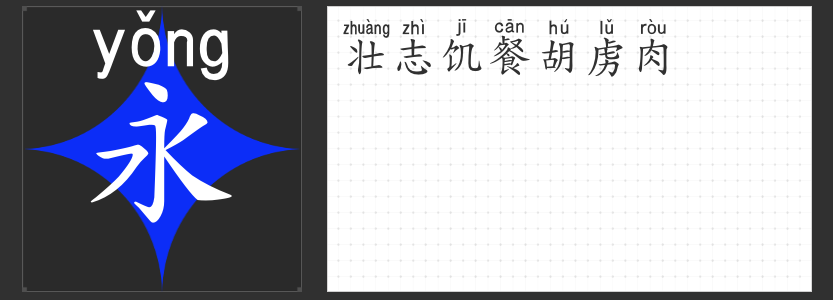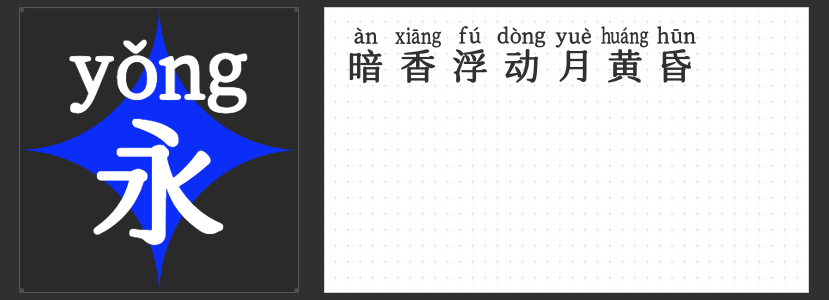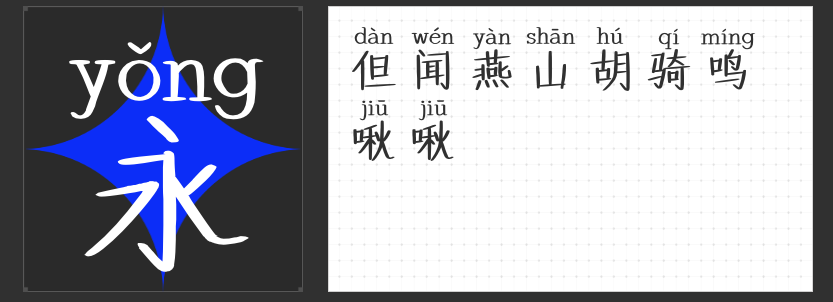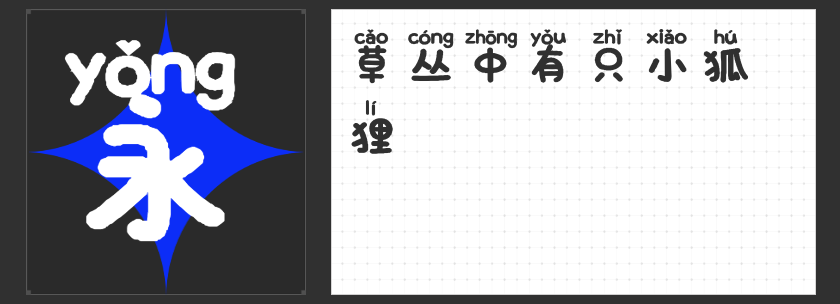
点亮童心:四款专为儿童图书设计的拼音字体
在儿童图书的设计中,字体的选择至关重要。它不仅影响着阅读体验,更是激发孩子学习兴趣的关键因素之一。今天,我们将介绍四款专门为儿童图书设计带有注音的字体。这些字体在保证清晰易读的同时,可以通过拼音认识新字,旨在为孩子们带来更好的阅读体验。
1. 字圈也字仿宋拼音
“字圈也字仿宋拼音”是一款基于传统仿宋体的拼音字体,它保留了仿宋体的简洁线条和端正笔画,同时添加了清晰的拼音标记。这款字体非常适合用于儿童的初级阅读材料,如启蒙读物或故事书。它的设计风格既传统又不失现代感,能够帮助孩子轻松识别汉字和拼音,从而培养良好的阅读习惯。
2. 字圈也字教科书拼音体
作为一款专为教学设计的拼音字体,“字圈也字教科书拼音体”采用了更为规范和标准的笔画结构。它通过清晰的字形和易于区分的拼音标记,使儿童在学习过程中能够更加专注。无论是教材还是练习册,这款字体都能为孩子们提供一个舒适的学习环境,让他们在学习汉字的同时,也能轻松掌握正确的发音。
3. 字圈也字楷书拼音
对于喜欢书写的孩子来说,“字圈也字楷书拼音”是一个不错的选择。这款字体融合了楷书的优美和拼音的实用性,既能激发孩子的审美情趣,又能帮助他们更好地理解汉字的书写规则。此外,其拼音部分设计得格外醒目,使得孩子们在阅读时能够迅速捕捉到拼音信息,提高阅读效率。
4. 字圈也字绘本拼音体
最后,我们来谈谈“字圈也字绘本拼音体”。这款字体特别适合用于儿童绘本,它的设计风格充满了童趣和想象力。无论是汉字还是拼音部分,都采用了柔和的曲线,能够吸引孩子们的注意力,激发他们的阅读兴趣。使用这款字体的书籍不仅能让孩子们在享受阅读的乐趣中学习新知识,还能培养他们的创造力和艺术鉴赏力。
字体虽然看似微小,但它在儿童图书中的作用却是举足轻重的。以上推荐的四款拼音字体,不仅注重了字体本身的功能性和美观度,还充分考虑到了孩子们的心理特点和发展需求。选择合适的字体,能够让孩子在快乐的氛围中成长,为他们的未来打下坚实的基础。让我们一起为孩子们挑选最适合的字体,点亮他们的阅读之旅吧!